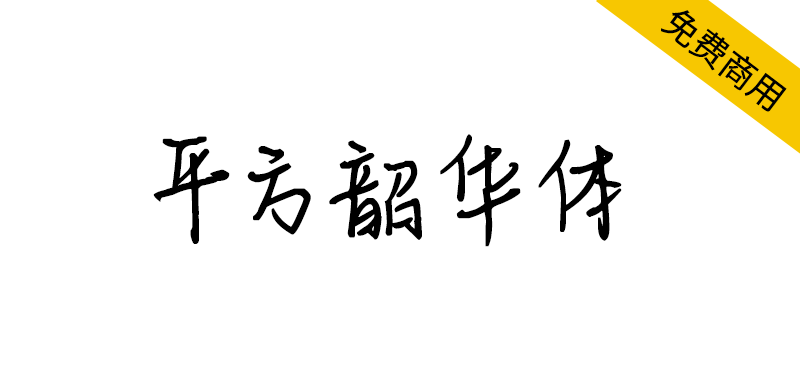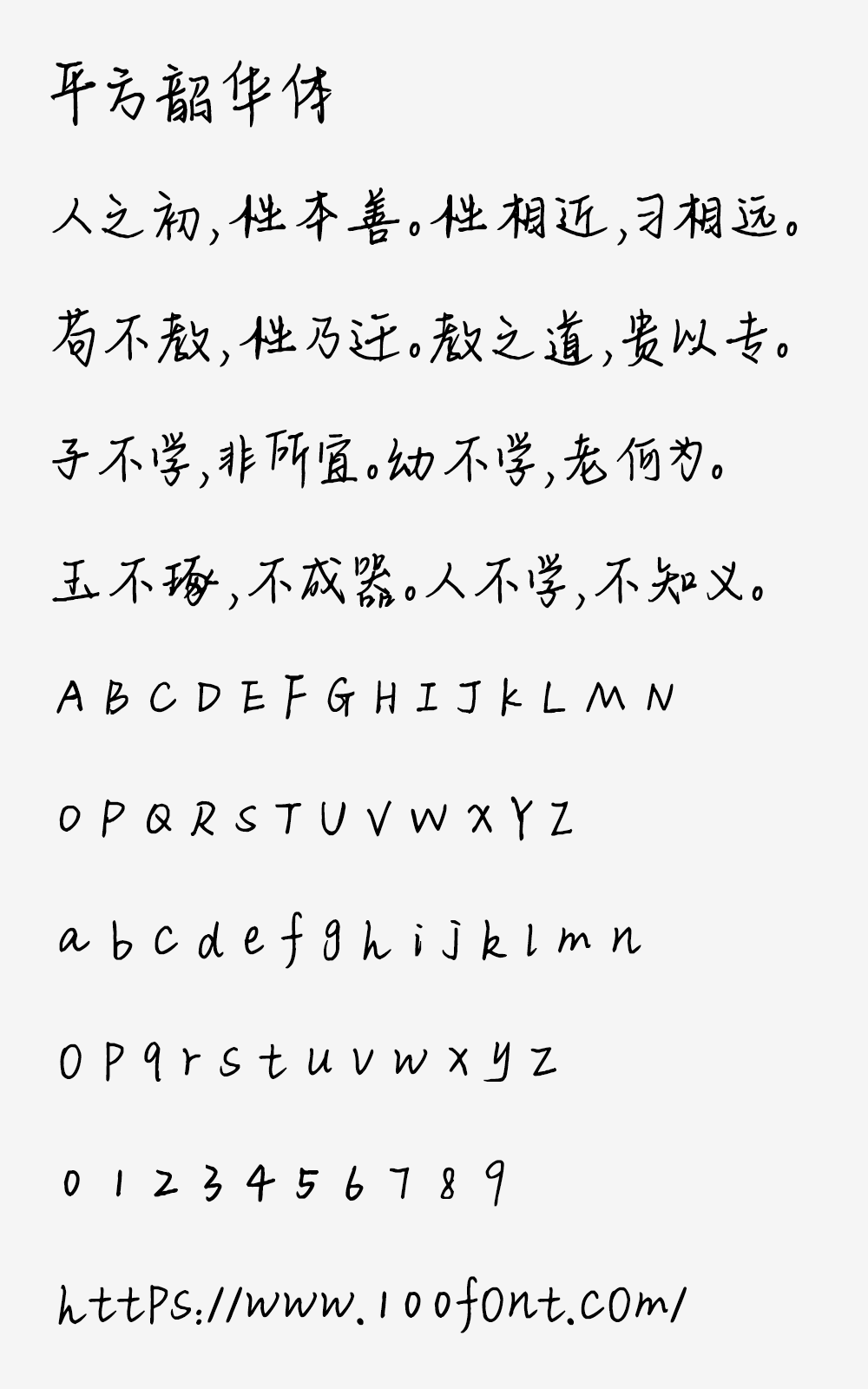
【平方韶华体】笔画粗细匀称,书写自然流畅的手写体字体
探寻一款兼具艺术美感与实用性的手写字体?平方韶华体以其笔画匀称、书写流畅的特点,为你的创作注入优雅灵魂。这款字体不仅适用于艺术创作、平面广告和书法练习,更令人惊喜的是,它允许个人和企业免费商用!了解如何正确使用这款字体,让你的设计作品脱颖而出,同时避免版权陷阱。
【平方韶华体】笔画粗细匀称,书写自然流畅的手写体字体
平方韶华体是一款笔画粗细匀称,书写自然流畅的创意手写体字体,呈现出优雅的视觉美感,具有广泛的应用性,适合艺术创作、平面广告及书法练习等场景
【平方韶华体】笔画粗细匀称,书写自然流畅的手写体字体